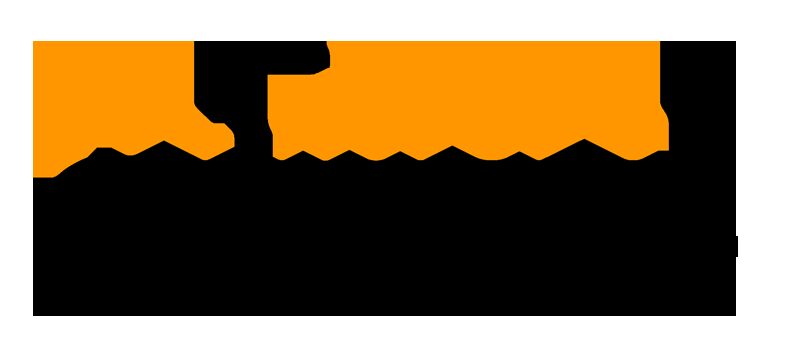
Ten krój pisma odzwierciedla tradycyjne pismo bugijskie, używane przez Bugijczyków – lud żeglarski pochodzący z południowego wybrzeża południowego Sulawesi. Bugijczycy przeprawiali się do innych regionów na tradycyjnych łodziach typu phinisi.
Południowo-zachodni półwysep Sulawesi jest domem dla trzech spokrewnionych ludów żeglarskich: Makasarów na południowym zachodzie, Mandarów na północnym zachodzie oraz Bugijczyków, którzy zajmują większą część pozostałego terenu półwyspu. Grupy te dzieliły podobny system pisma oraz pluralistyczny system polityczny, w którym lokalne władze były powiązane z obdarzonymi nadprzyrodzoną mocą regaliami (arajang) i wywodziły swoje pochodzenie od różnych mitycznych przodków, z których każdy uchodził za istotę zstępującą z nieba (tomanurung).
W latach 1600–1669 miasto Makassar oraz rządzące nim dynastie Gowa-Tallo zdominowały region politycznie i gospodarczo. Urażeni Bugijczycy z królestwa Bone połączyli siły z VOC, aby w 1669 roku zniszczyć Makassar. Wydarzenie to miało co najmniej dwie konsekwencje. Po pierwsze, Bone stało się najważniejszym królestwem w południowo-zachodnim Sulawesi aż do XIX wieku. Po drugie, doprowadziło ono do migracji i diaspory Bugijczyków, zwłaszcza wśród mężczyzn z Wajo, którzy podczas wojny sprzymierzyły się z makasarskim Gowa zamiast z Bugijczykami z Bone. Bugijczycy stali się znani jako wojownicy i handlarze w całym Archipelagu.